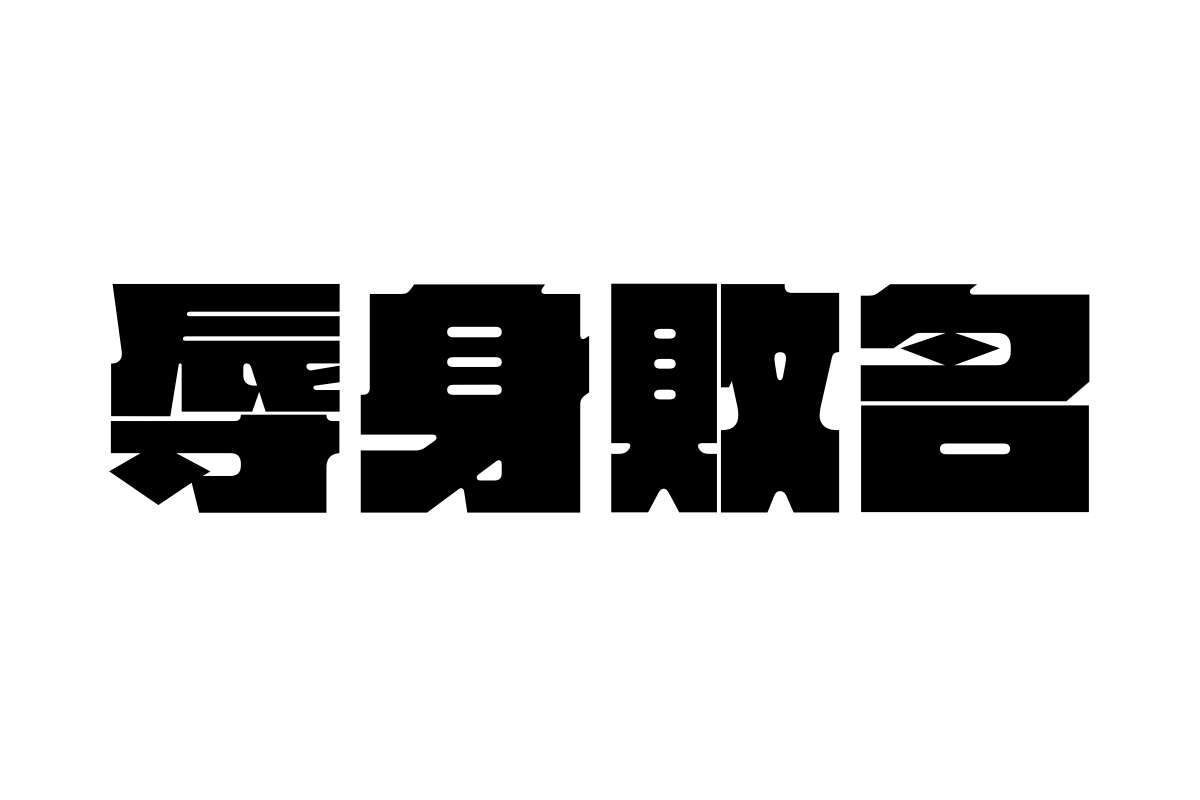
汉仪方墨体繁是一种具有独特风格的中文字体。这种字体以其简约、现代的设计风格而受到许多人的喜爱。它的笔画清晰,结构紧凑,给人一种简洁明了的感觉。同时,汉仪方墨体繁也具有一定的艺术感,能够很好地展示文字的魅力。
这种字体的特点是线条流畅,结构紧凑,给人一种简洁明了的感觉。它的笔画清晰,结构紧凑,能够很好地展示文字的魅力。此外,汉仪方墨体繁还具有一定的艺术感,能够很好地展示文字的美感。
总的来说,汉仪方墨体繁是一种非常实用的中文字体,无论是在正式的文件还是非正式的聊天中,都能够很好地展示出文字的魅力。